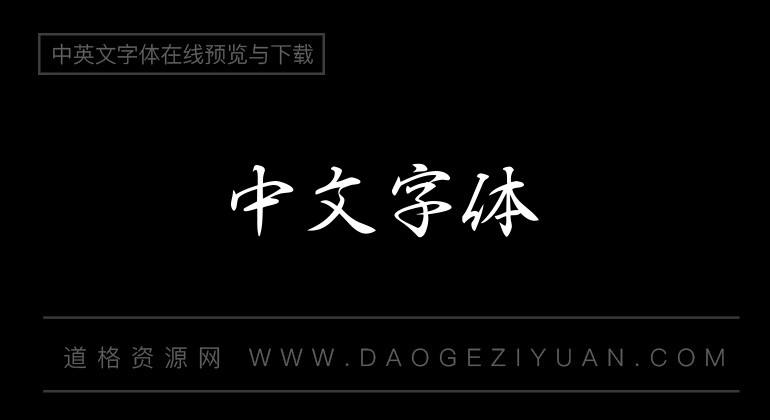
? 白舟行书pro教汉是一款由白舟字体设计团队精心打造的中文字体,它以简洁大方的风格,清新优雅的线条,为用户提供一种更加优雅、简洁、大方的体验。白舟行书pro教汉字体有着清新优雅的线条,拥有良好的可读性,适用于网页、报纸、书籍、广告等多种文档的设计。文件名:hkgyoprokk-1.ttf
白舟行书pro教汉是一款非常不错的手写艺术字体,具有很好的视觉感,适合于文化类的宣传设计、商业类品牌的广告和产品包装设计以及个性化文字排版等较多场景。